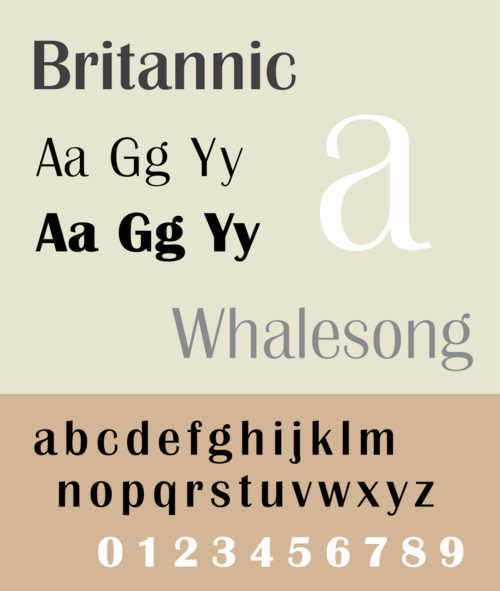
| カテゴリ | サンセリフ |
| 分類 | 変調グロテスク |
| 鋳造所 | スティーブンソン・ブレイク |
Britannic は、スティーブンソン・ブレイクが金属活字で販売していたサンセリフ 書体ファミリーです。これは「変調」または強調されたサンセリフデザインで、縦線が横線よりも明らかに太くなっています。[1] [2] [3]クリングスポル博物館によると、この書体はもともとドイツのライプツィヒにある Wagner & Schmidt 鋳造所で作成されたとのことです。[4] [5]デザイン上、この書体は本文の連続テキストではなく、見出し、広告、看板用に意図されています。スティーブンソン・ブレイクはこれを「広告やディスプレイパネルに最適な書体」として宣伝しました。[6]
スティーブンソン・ブレイクはデジタルフォント事業を継続しなかったため、様々な企業によって、様々なウェイトと幅のブリタニック書体のデジタル化がリリースされている。[7] [8] [9]一部のリリースには、すべて大文字のコンデンスウェイトが含まれている。[7] URWによってデジタル化されたボールドウェイトは、 Officeなどの一部のMicrosoftソフトウェアに付属している。おそらくMicrosoftのタイポグラフィマネージャーであるロバート・ノートンによると思われるデザインに関する皮肉な解説には、次のように付け加えられている。
この興味深い書体は常に激しい意見を巻き起こします。筆者のように、ブリタニック ボールドを「記念碑的に過大評価されている」というカテゴリーにしっかりと入れている人もいます。また、それを断言する人もいます。実際、多額の費用をかけて行われた調査 (3 人を対象に) では、3 人中 2 人がブリタニック ボールドは素晴らしいと考えていました。有名なスティーブンソン ブレイク書体鋳造所で誕生し、同じ鋳造所のロスベリー (ほとんどの人にとっては区別がつかないでしょう) よりも長く存続しているということは、すべてが悪いわけではないはずです... [10] [11] [検証失敗]
使用例
- イタリア軍( Esercito Italiano ) は、ロゴに Britannic Bold 書体を使用しました。